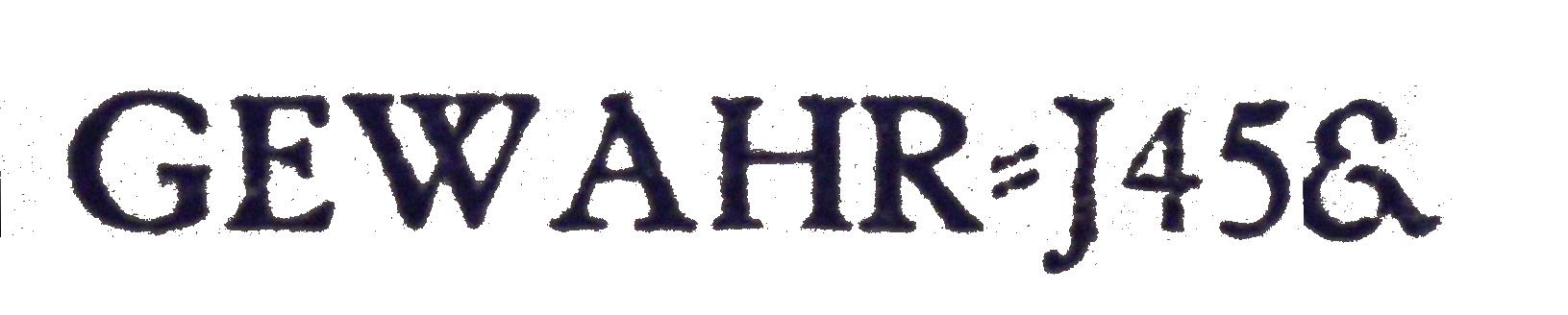
Alte Vergolderschrift
Ich hab vor kurzem drei Messing-Schriftsätze für's Handvergolden bei ebay erstanden und bekomme nicht raus, welche Schrift das ist. Hab's schon mit identifyfont usw. versucht. Am ehesten kommt noch "Garamond" hin, stimmt aber nicht ganz (z.B das "&" oder der doppelte Bindestrich).
Foto von den "typischsten" Zeichen: (die Schrift ist ca. 4 mm hoch, deshalb hier so unscharf)